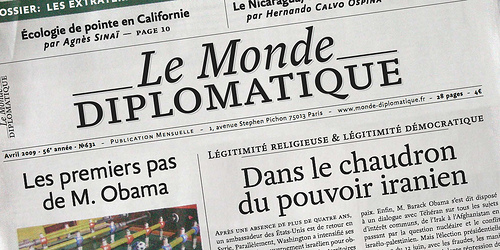
FF Yoga und FF Yoga Sans von Xavier Dupré
The FF Yoga family is a type system by Xavier Dupré conceived for newspapers and magazines thanks to its strong personality and good legibility.
FF Yoga, with its sturdy serifs is a good choice for body text, but it also serves as an original headline face with its subtly chiseled counters. The face mixes the dynamic tension of straight cuts with the balanced rhythm and elegant curves of Garalde typefaces.
FF Yoga Sans is a contemporary alternative to Gill Sans and a sober companion to the serif FF Yoga.
Die aktuelle Ausgabe des Design-Made-in-Germany-Magazins enthält ein kleines Interview mit Xavier Dupré zur FF Yoga (HTML | PDF)
habe ich einen knick in der optik oder ist das eine schräge sache? die kursive, insbesondere der sans, kommt mir (zu) stark geneigt vor. das dürften so 15–16 grad sein, also etwa doppelt so viel wie bei der kursiven gill sans, die ja offenbar pate gestanden hat. bei einigen buchstaben der yoga sans habe ich angst, dass sie nach rechts umfallen. müsste man sich mal in textgrößen anschauen, aber isoliert betrachtet wirkt das für eher missglückt. sehe nur ich das so?
missglückt würde ich es nicht nennen, ist halt mal was anderes. vielleicht soll es ja ein eigener character sein, die schrift wurde ja für zeitungen und magazine entworfen und da will man sich ja gerne von mitbewerben etwas absetzen.
aber das die gill hier pate gestanden hat sehe ich auch so, der sans-schnitt ist daher irgendwie nicht so mein fall. ich mag dieses humanistische a einfach nicht.
mit ›missglückt‹ meine ich nicht, dass dupré etwas versucht und mangels können nicht erreicht hat. sauber gearbeitet sind auch die umfaller. ich ?nde nur die entscheidung für eine so schräge kursive falsch. das ergebnis ist meiner ansicht nach sonderbar. absetzen kann man sich so bestimmt von anderen schriften, die eben eine kursive mit vernünftiger neigung haben.
gibt es eigentlich groteskschriften, bei denen sich die kursive – wie bei manchen antiquæ – nicht durch die neigung, sondern nur durch die zeichenform von der aufrechten unterscheidet?
Die Quadraat Sans hat zum Beispiel eine recht kleine Schräglage.
Die Auto-1-Familie von Underware kommt in der Kursiven auch relativ aufrecht daher.